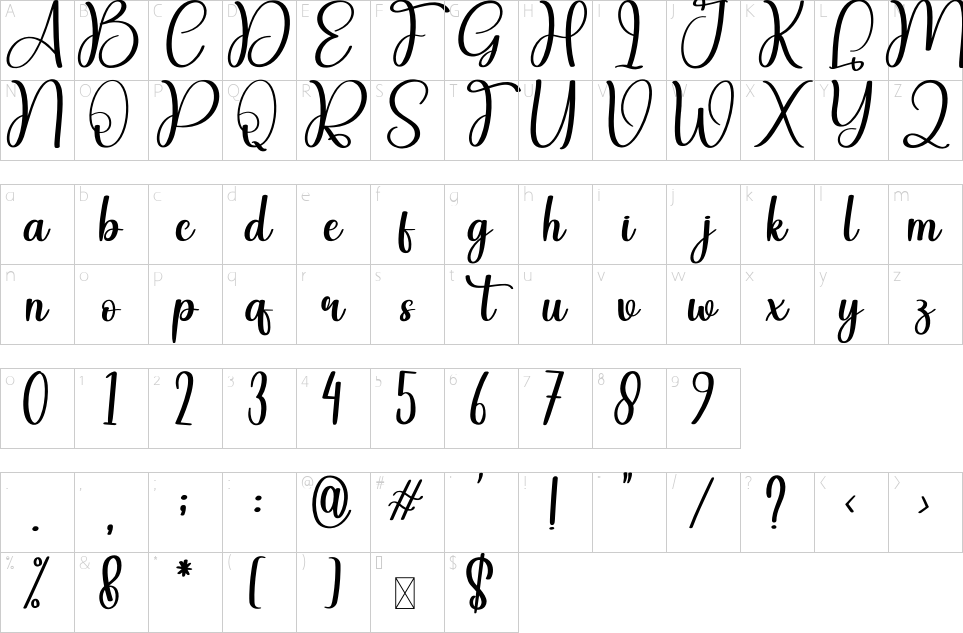
Descubra a Delightful Font, uma elegante e fresca opção para personalizar seus documentos, apresentações ou qualquer projeto digital do seu dia-a-dia. Desenvolvida por scratchones, essa fonte está disponível gratuitamente tanto para sistemas Windows quanto Mac. Com traços suaves e linhas levemente onduladas, Delightful pode ser a escolha perfeita para aqueles que desejam um toque de simplicidade na sua tipografia. Seja você designer ou amante do design, o sucesso está no clique – baixe seu exemplar da Delightful Font hoje e deixe seu trabalho brilhar com este charmoso traço único. Com mais de 687 downloads desde sua criação, é evidente que esta font tem algo especial para oferecer aos amantes do design como você.